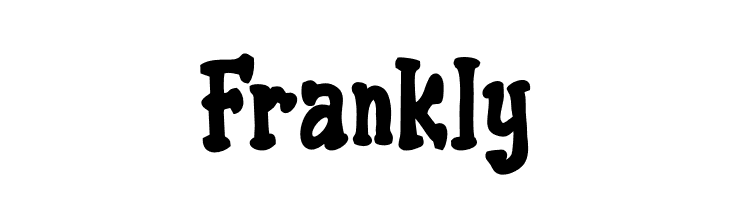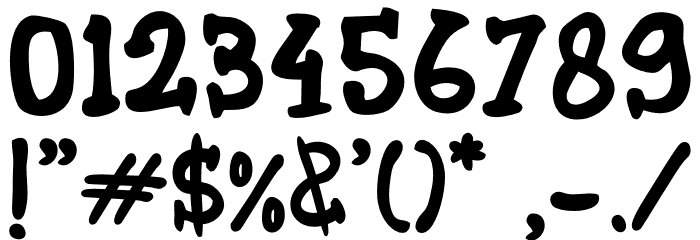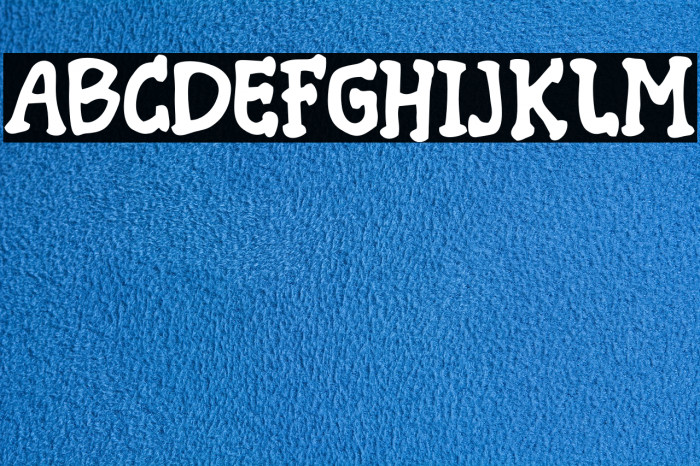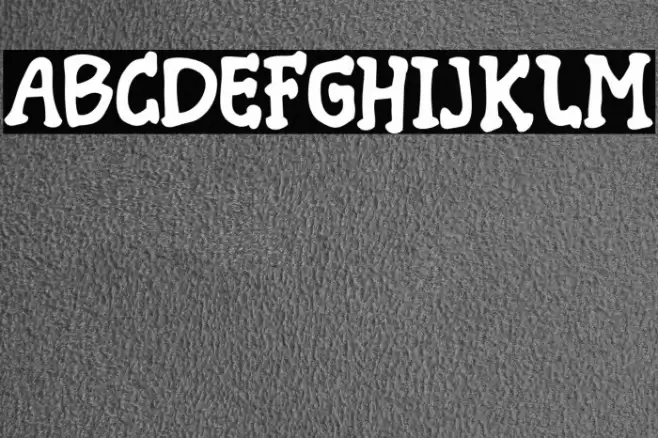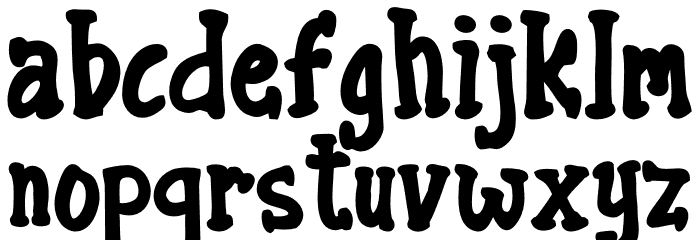
Frankly Font
| समग्र शैली | Playful, Whimsical, Cartoon-like |
| उपयोग का मामला | Headlines, Logos, Posters, Invitations |
| सुझाए गए प्रोजेक्ट | Ideal for children's books, comic strips, playful branding, party invitations, and any project requiring a fun, informal touch. |